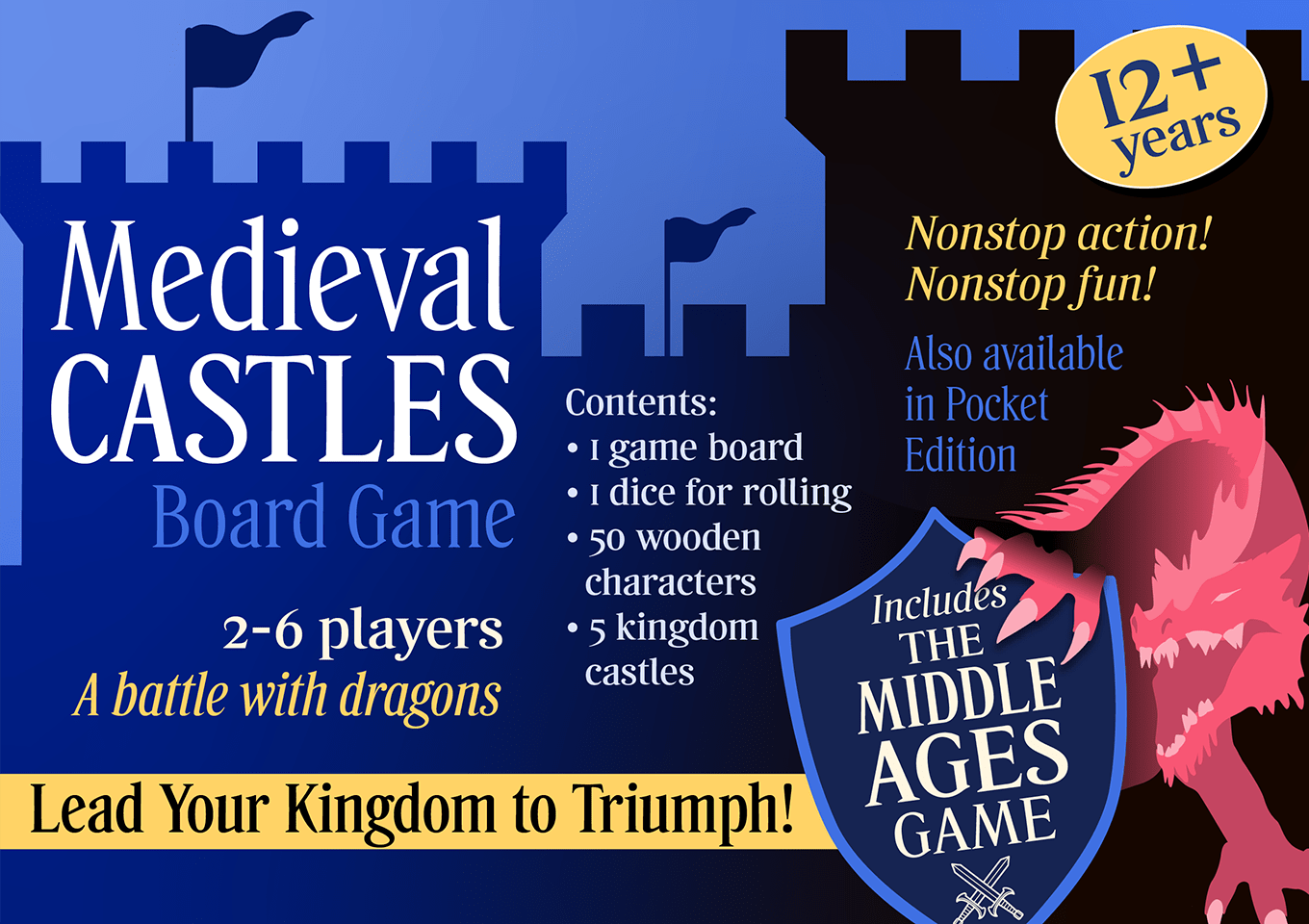
主に19世紀に見られた伝統的なウェッジセリフ体を再解釈したディスプレイ書体です。鋭利で繊細なセリフに腰高で独創的な骨格を合わせることで、中世の芸術活動を想起させるデザインに仕上げています。伝記や歴史小説など文化的な書籍装丁などでの利用に最適です。 通常の字幅に加え、見出し利用に最適な長体のCondensedも用意されています。